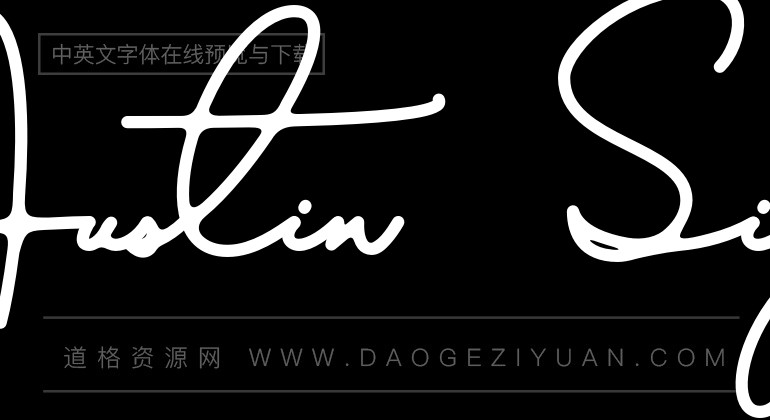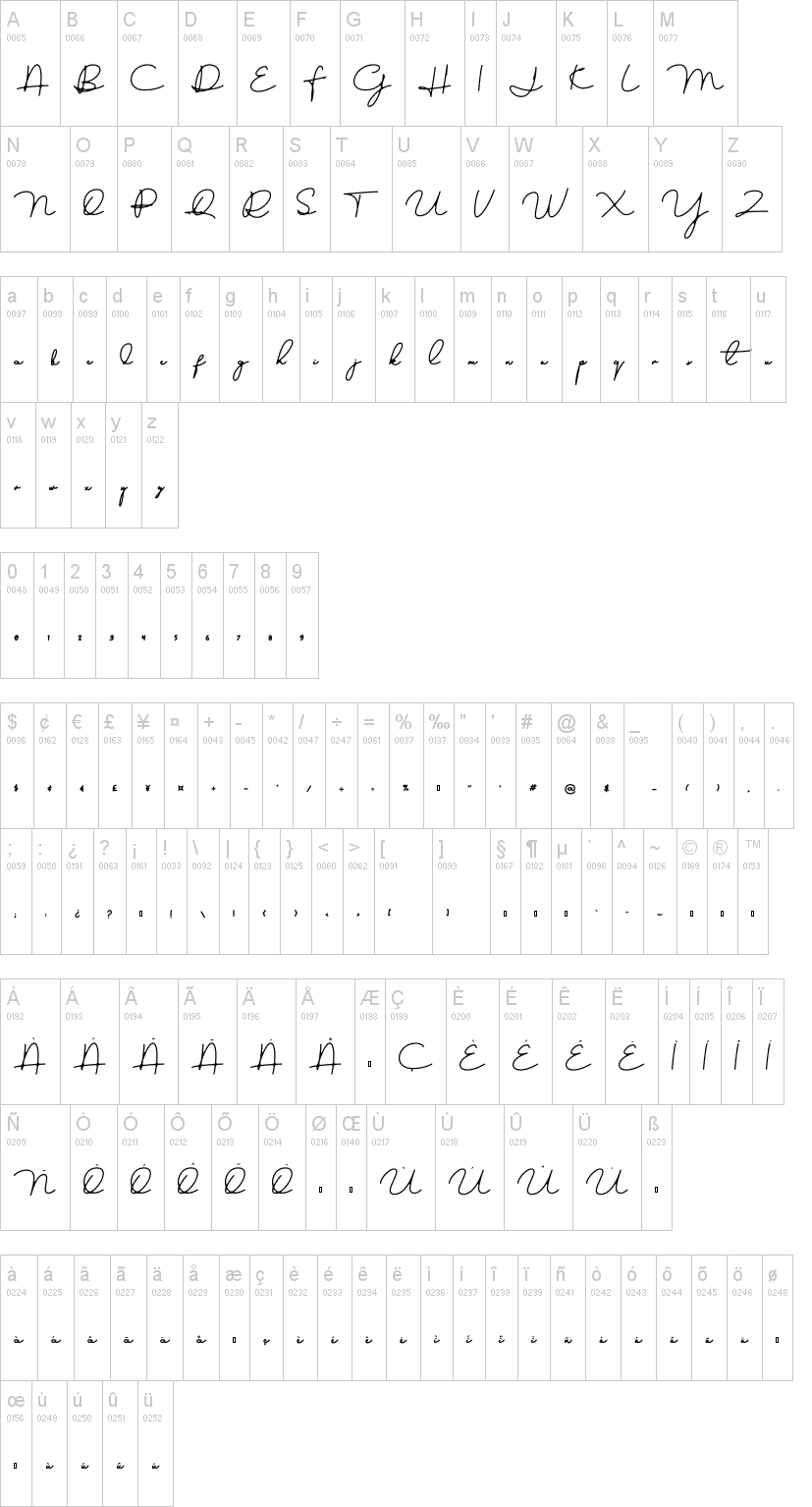
Austin Signs
Austin Signs字体是一款经典的古典字体,它拥有传统的英国复古风格。它的字体笔画细腻,线条流畅,字形大小合理,有着深厚的历史渊源,是一种很受欢迎的字体。它的字体有着浓厚的古典风格,可以让文字更加精致,且字体的设计也更加精细,可以更好地表达文字的意义。它可以用于创作海报、书籍和宣传单等,可以为文字添加更多的深度和精致。
Austin Signs是一款非常不错的手写艺术字体,具有很好的视觉感,适合于文化类的宣传设计、商业类品牌的广告和产品包装设计以及个性化文字排版等较多场景。
Austin Signs字符映射图